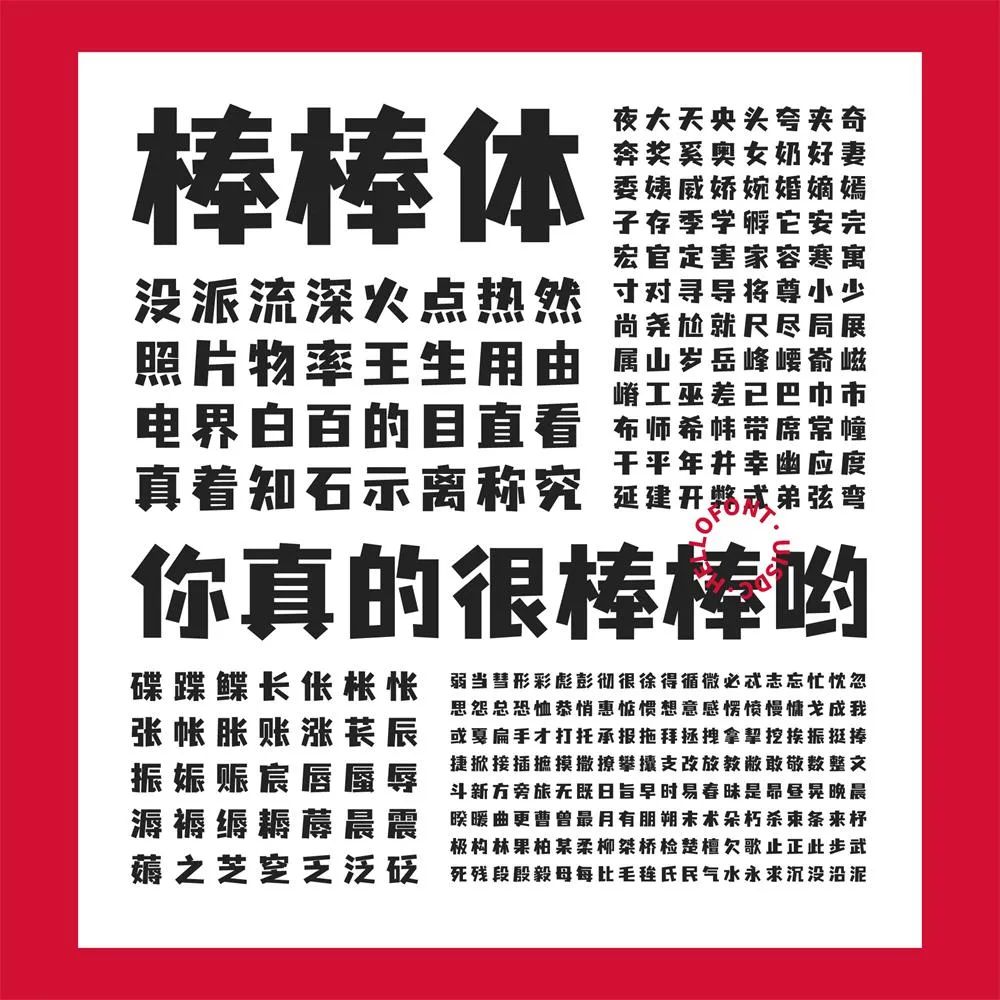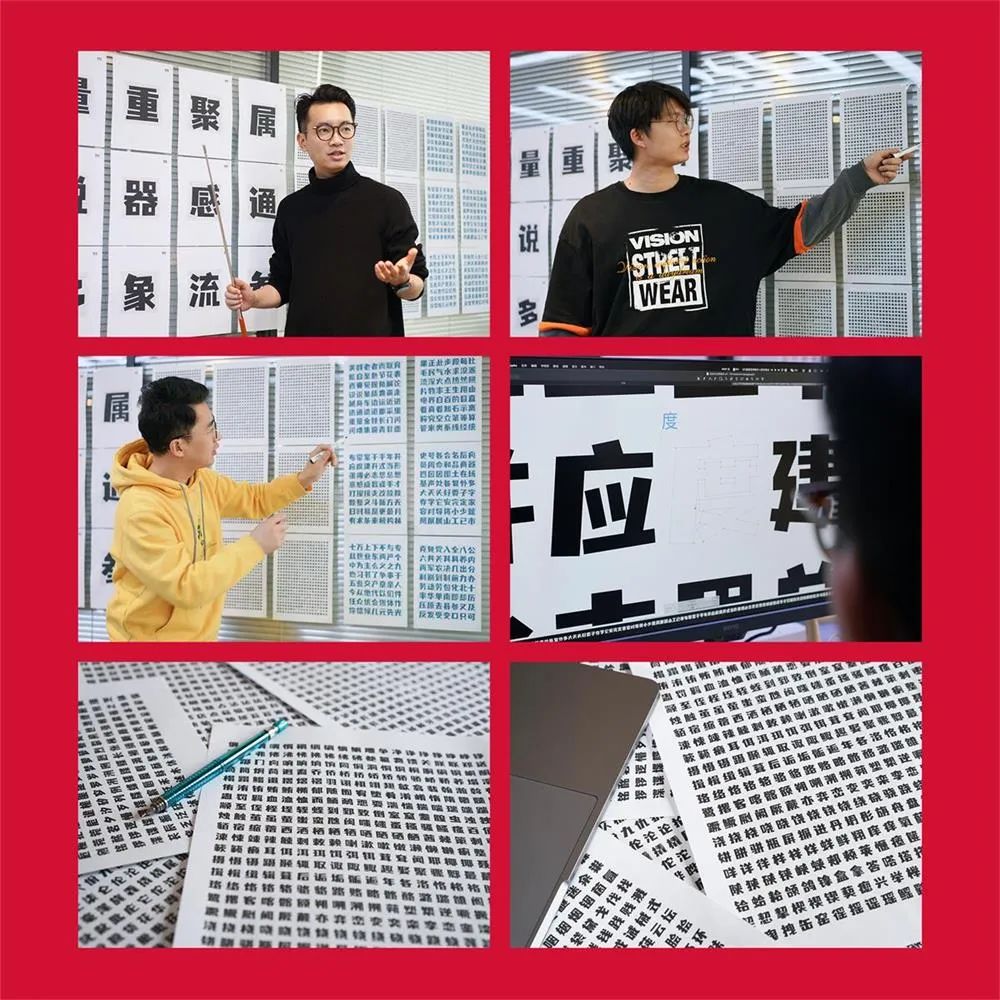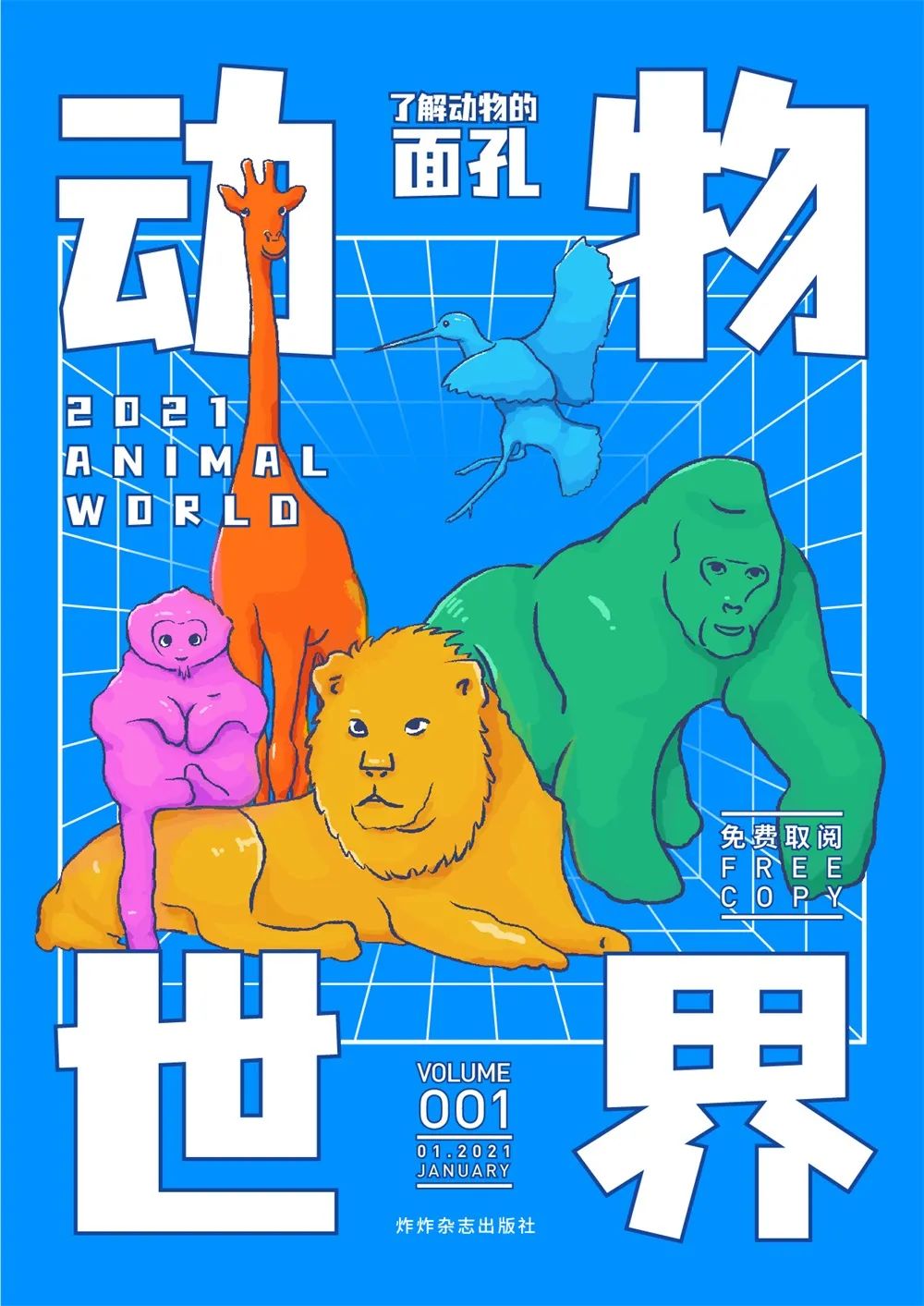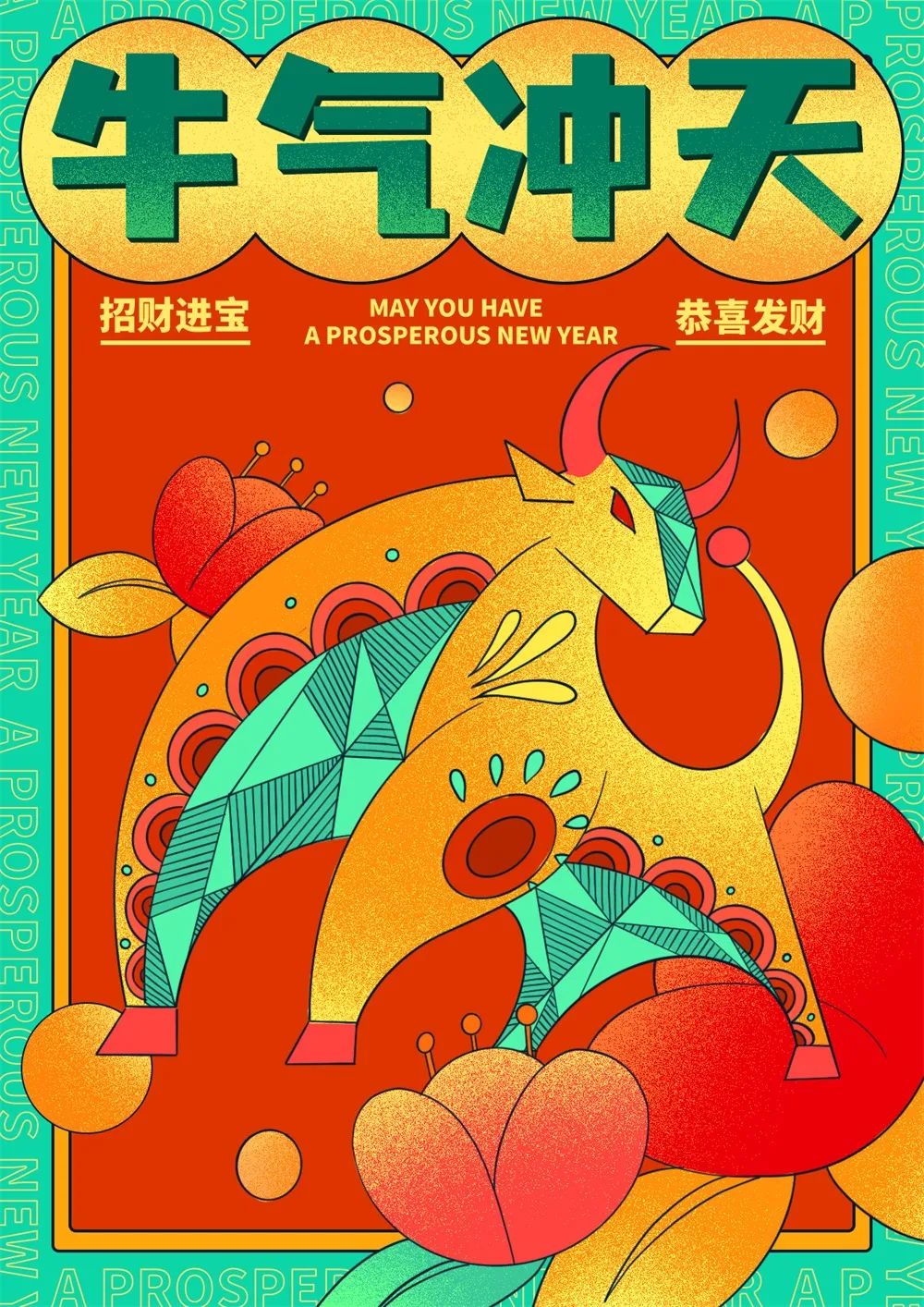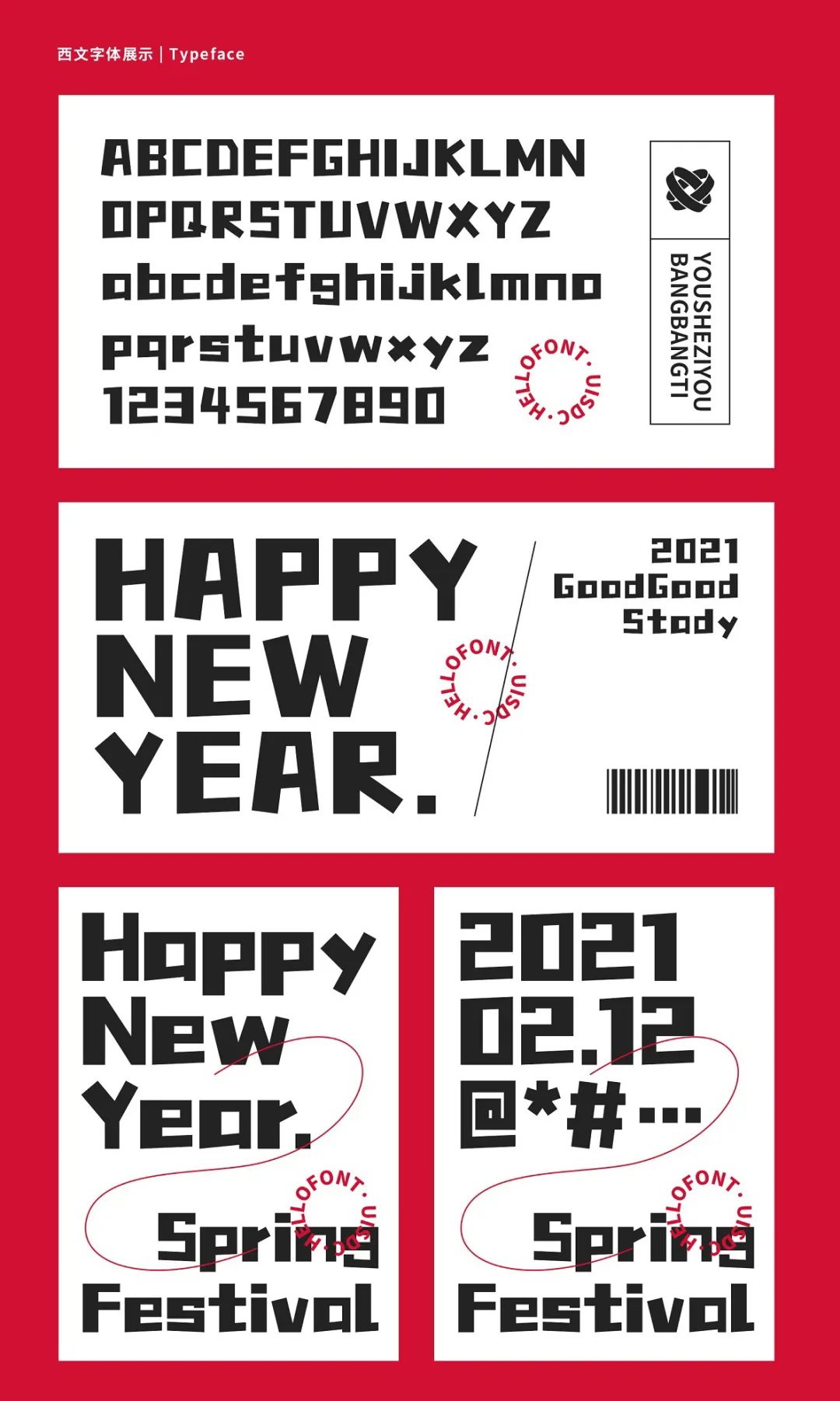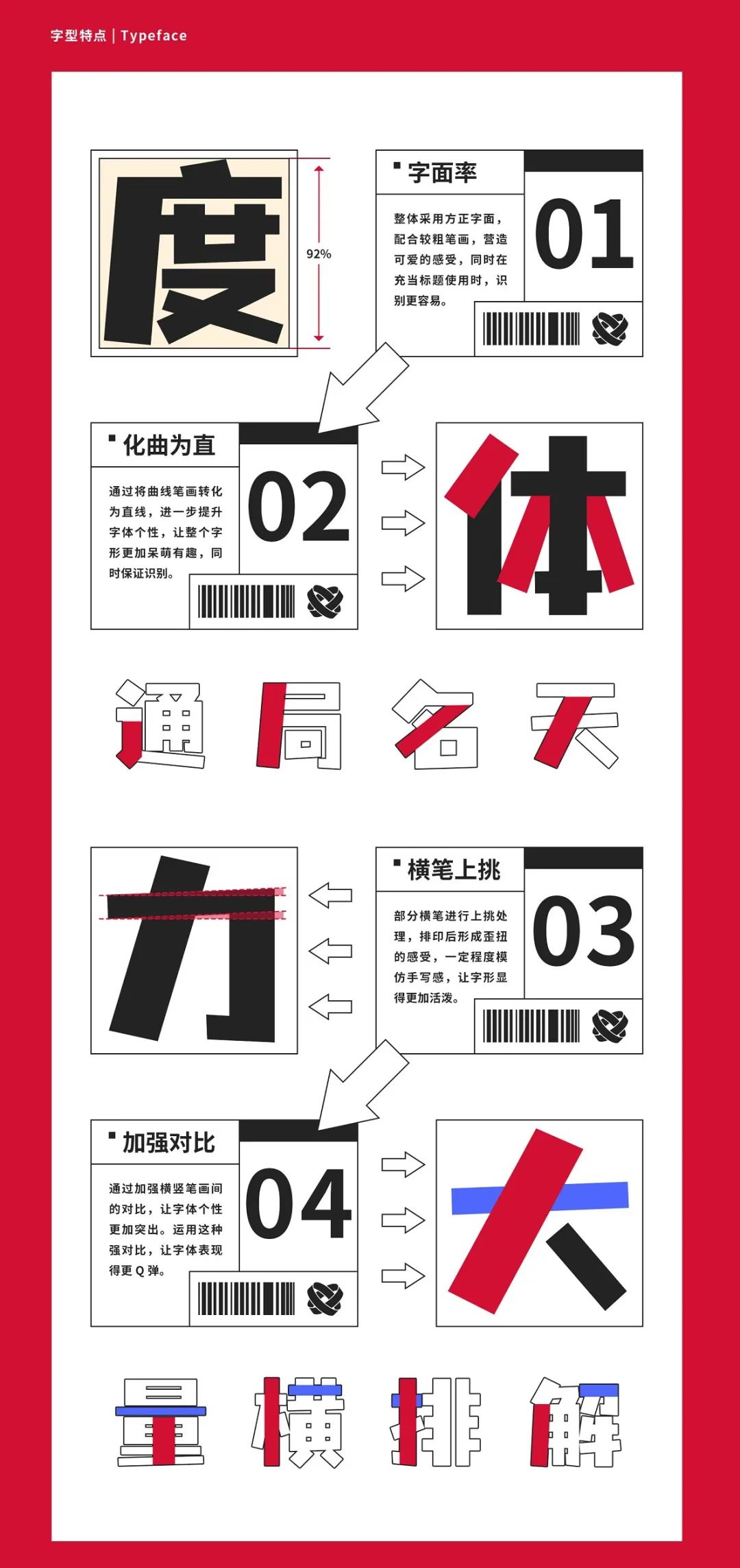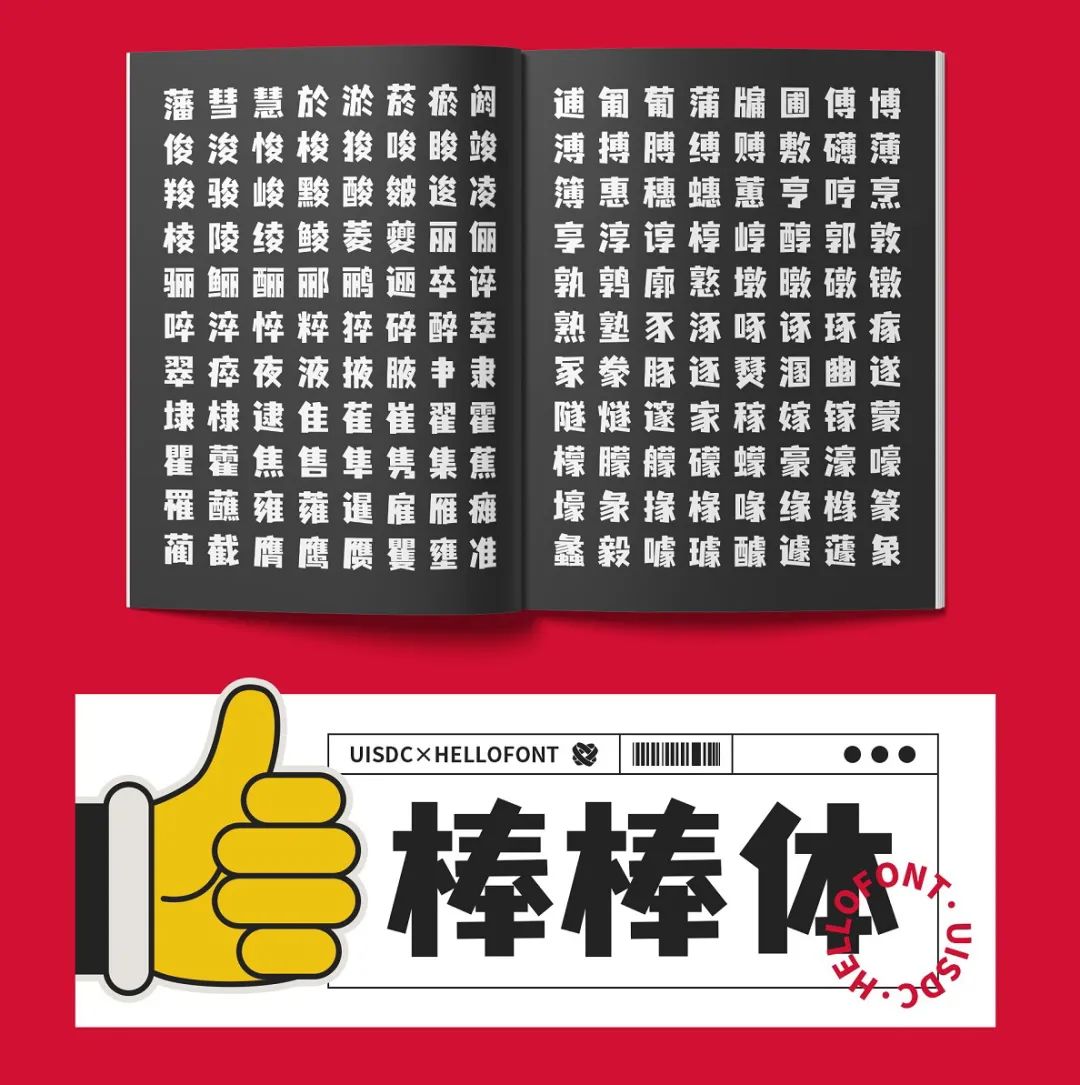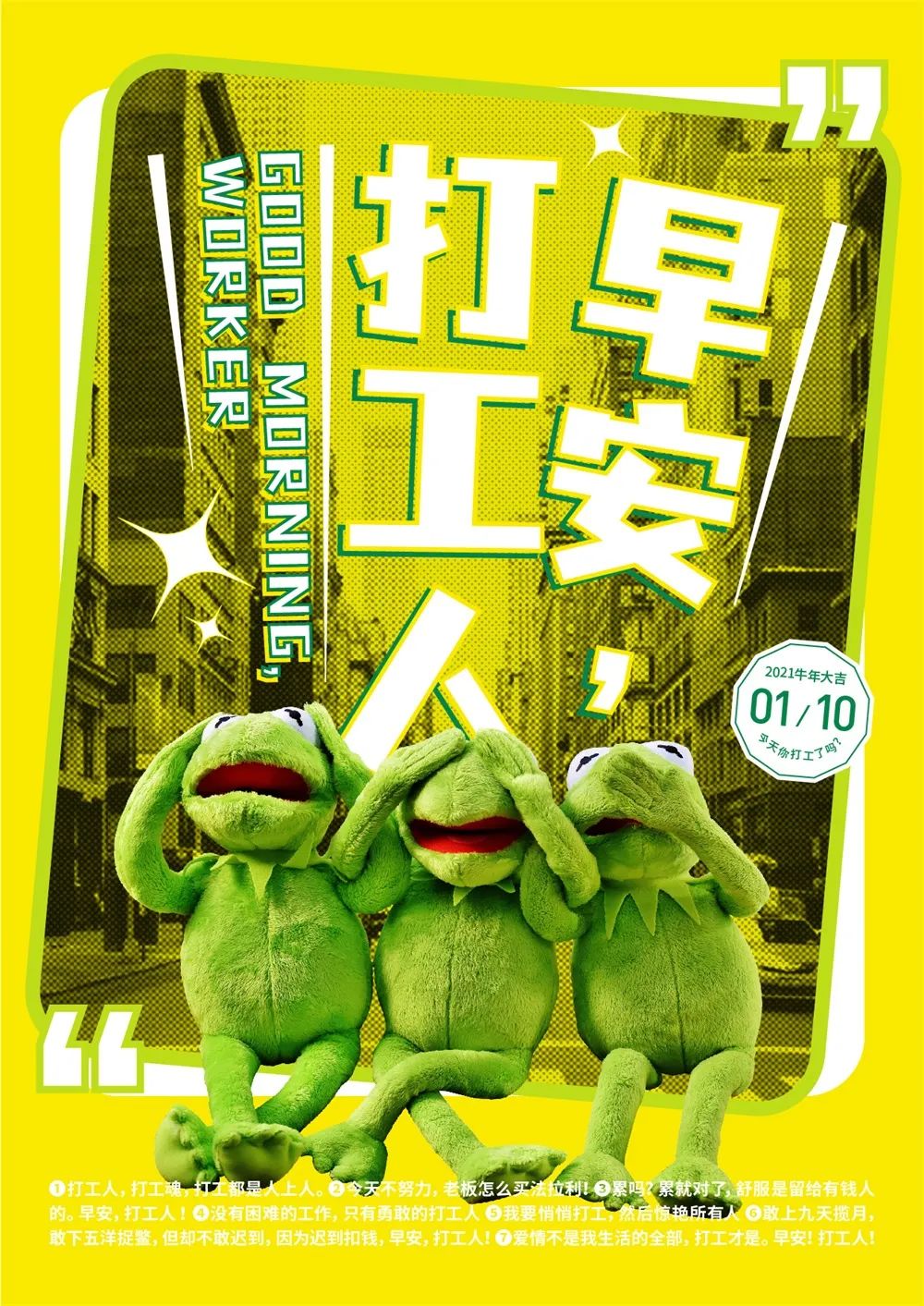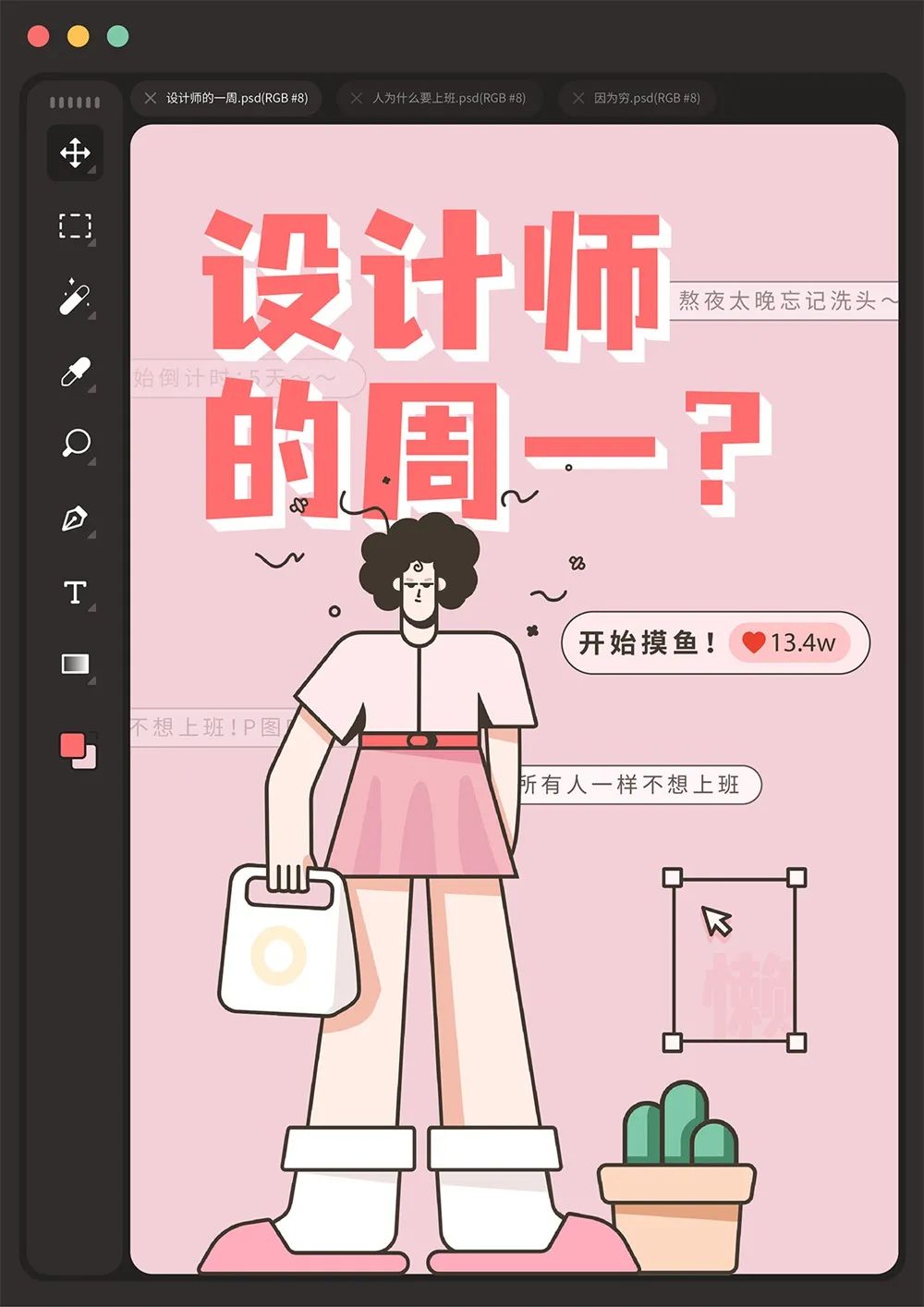
惊喜空降!字由X优设第三款免费商用字来啦~
今天凌晨看到消息的小伙伴,肯定是一脸懵,优设字由棒棒体,这么突然的吗?
哈哈哈,其实早在字由X优设合作初期,就定下了三款字的免费基调,只是因为疫情,时间稍微延后了一些,不过也正因如此,让我们年年有惊喜。
不管是火遍全网的优设标题黑,还是被电商追捧的优设好身体,都一次次证明了字由X优设的强大实力,所以第三款免费字,很多人早就翘首以待了。
确实棒,那就叫棒棒体?开玩笑,之所以叫这个名字,一方面是前两款字收获了太多的好评,最后一款就想着回馈你们,祝你们 2021 工作棒棒,身体棒棒,牛年棒棒。另一方面,字体本身的结构也比较像棒子组成的笔画,叠起来叫有一种轻松可爱的感觉。
说完了棒棒的诞生,下面说说它的风格,有前两款偏力量和柔美的珠玉在前,第三款怎么能别具一格,又广泛适用于日常的工作需求呢?为此字由和优设经过了多次讨论,最终从 3 个版本中,敲定了这款可爱风的字体雏形。
之后优设做了 300 多个基础字型、字母及符号的创意与规范后,字由继续从字库角度出发,完成了 6000 多个字型的制作,这其中包括阿里巴巴普惠体的设计师陶一泓、汉仪阿尔兹海默病体设计项目负责人卢鑫亚、字由文艺黑的设计师石凯等。
「优设字由棒棒体」是一款集可爱、直率、俏皮为一体的专业美术标题字。在字型中,加强了“横细竖粗”的对比,提升文字张力;较大的字重,让其更加显眼;去掉字体中弯曲的笔画,用直线代替,增加了可爱、率真的感受;部分横笔做倾斜的处理,更为字体增添了一份俏皮。
为了让你们更好地用这款字,下面是应用场景展示,睁大你的眼睛哦~